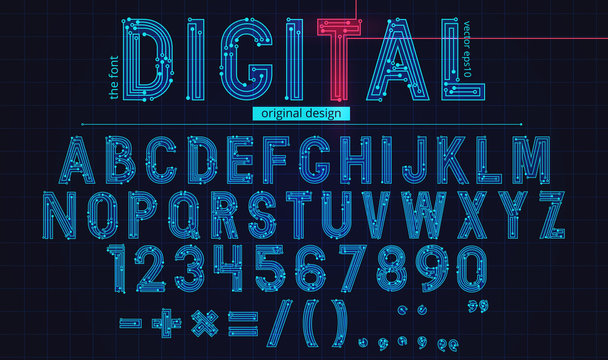
Font Digital miễn phí
Font Digital là một kiểu chữ mang đậm phong cách điện tử và hiện đại, thường gợi nhớ đến các màn hình LED hoặc LCD của những thiết bị kỹ thuật số. Với các đường nét góc cạnh, số hóa và thường là dạng mono-space, Font Digital tạo nên cảm giác công nghệ cao, phù hợp cho các thiết kế liên quan đến điện tử, viễn thông hoặc khoa học viễn tưởng. Sử dụng Font Digital thuộc bộ font chữ design trong các dự án thiết kế poster, logo hay giao diện người dùng sẽ mang lại sự độc đáo và ấn tượng mạnh mẽ, thu hút sự chú ý của người xem. Nếu bạn đang tìm kiếm một phông chữ để thể hiện tinh thần công nghệ và hiện đại, Font Digital chắc chắn là lựa chọn không thể bỏ qua.